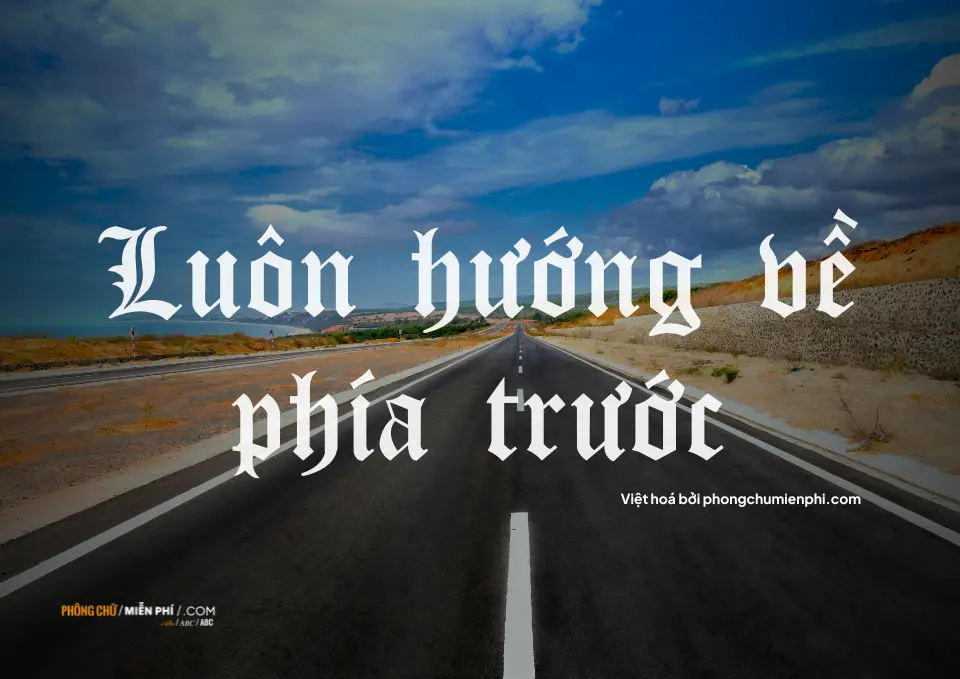
PCMP Cloister Black – Font chữ Việt hóa phong cách Old English cổ điển
PCMP Cloister Black là phiên bản font chữ Việt hóa của kiểu chữ Old English / Blackletter nổi tiếng, mang đậm hơi thở cổ điển và sự trang nghiêm. Với các đường nét sắc sảo, cấu trúc góc cạnh cùng những chi tiết trang trí tinh tế, font này đem lại cảm giác mạnh mẽ, uy nghi nhưng vẫn đầy tính nghệ thuật.
Phiên bản Việt hóa do Phong Chữ Miễn Phí (PCMP) thực hiện, giúp font hỗ trợ đầy đủ bộ ký tự tiếng Việt, đảm bảo tính thẩm mỹ khi sử dụng trong các thiết kế dành cho thị trường Việt Nam.
Đặc điểm nổi bật
Phong cách cổ điển: Dựa trên thiết kế Gothic truyền thống, gợi nhớ đến các bản thảo châu Âu thời Trung cổ.
Nét chữ tinh tế: Đường nét dày, sắc và các chi tiết bo góc tinh xảo.
Hỗ trợ tiếng Việt hoàn chỉnh: Việt hóa chuẩn, giữ nguyên thần thái của bản gốc.
Ứng dụng đa dạng:
Thiết kế logo mang phong cách hoài cổ
Tiêu đề báo chí, bìa sách, tạp chí cổ điển
Thiệp mời, chứng nhận, bảng hiệu sang trọng
Các dự án thiết kế mang tính truyền thống, lịch sử
Lợi ích khi sử dụng PCMP Cloister Black
Tạo điểm nhấn sang trọng, khác biệt cho thiết kế
Phù hợp với nhiều lĩnh vực: xuất bản, quảng cáo, thương hiệu, lễ hội
PCMP Cloister Black là lựa chọn lý tưởng cho những ai yêu thích sự cổ điển, trang trọng và muốn thổi hồn lịch sử vào tác phẩm thiết kế. Với sự Việt hóa tinh tế, font vừa giữ nguyên bản sắc của bản gốc, vừa đáp ứng nhu cầu sáng tạo của người dùng Việt Nam.